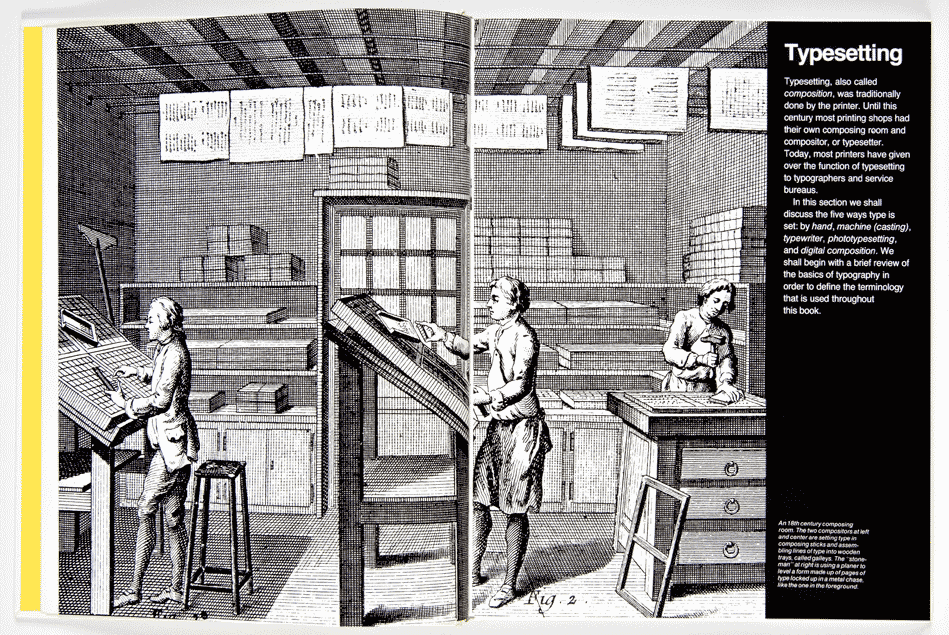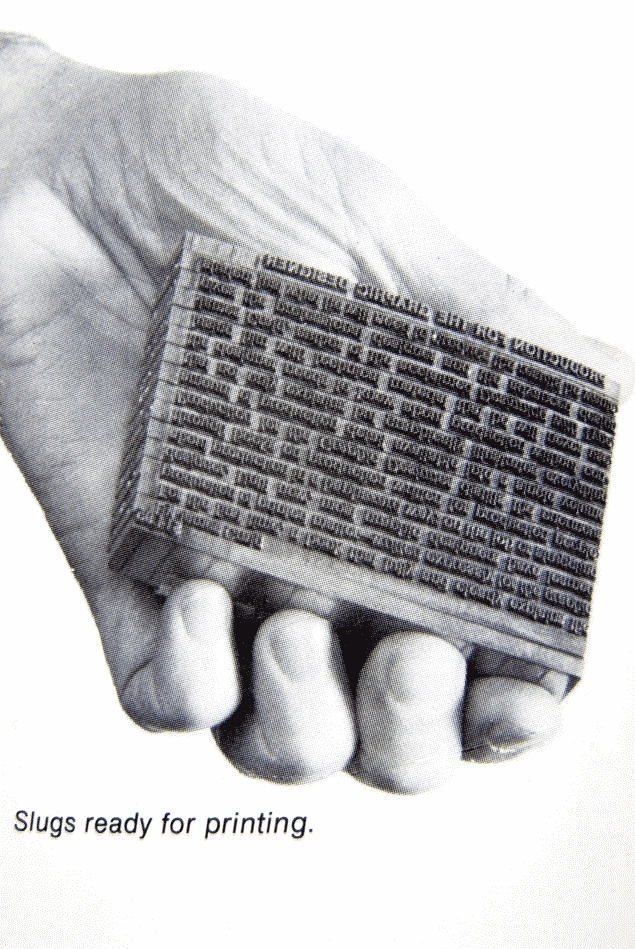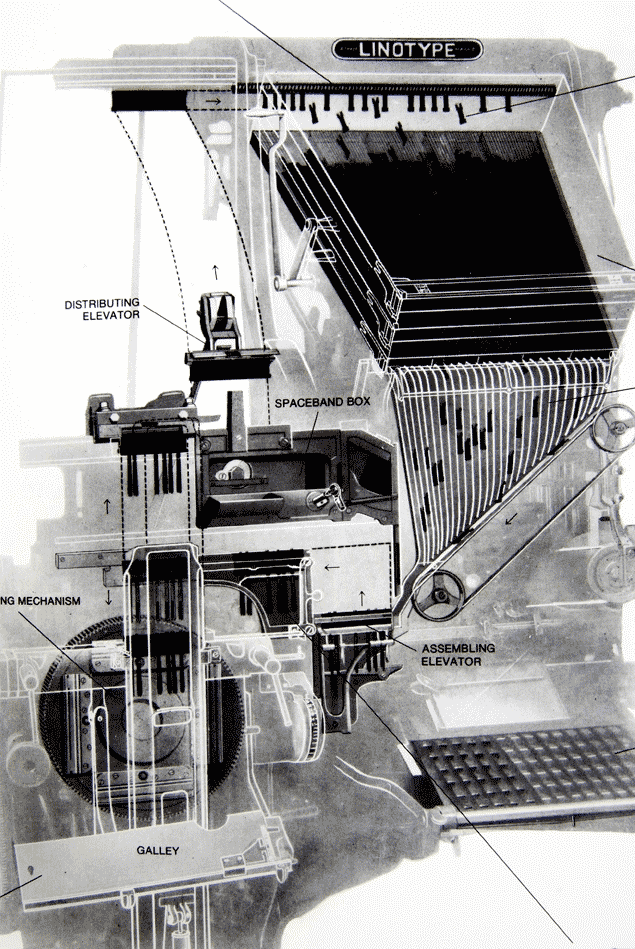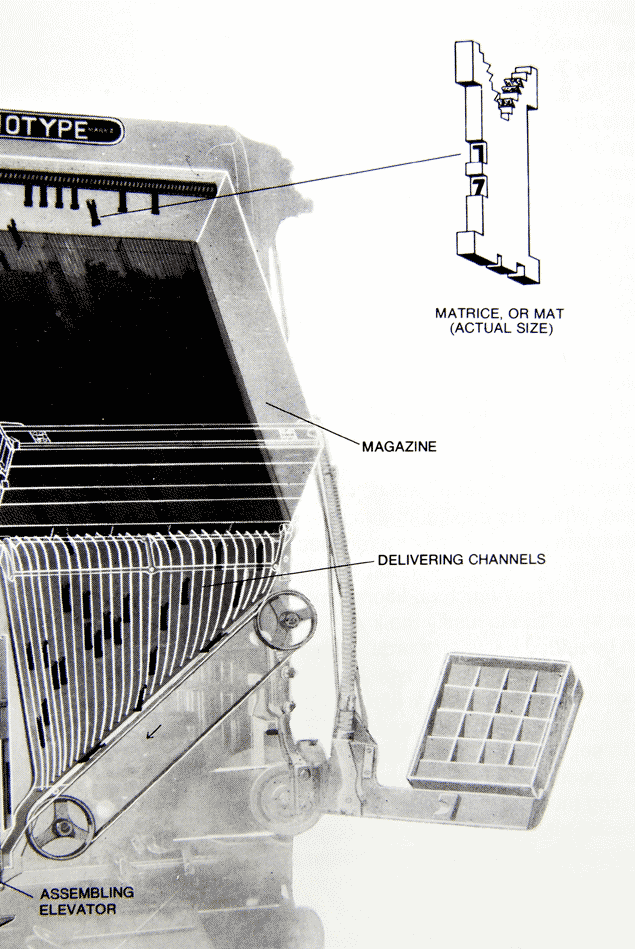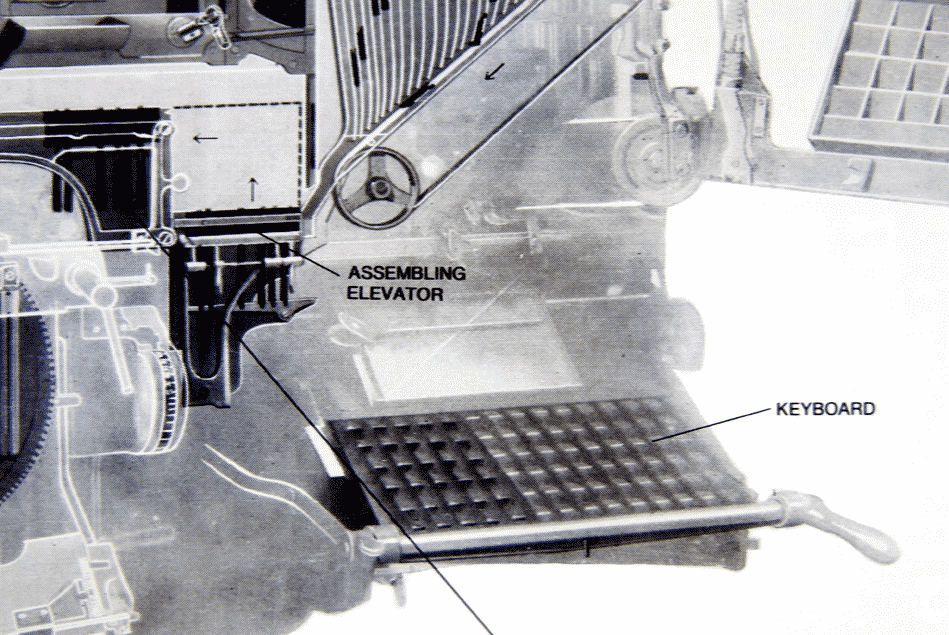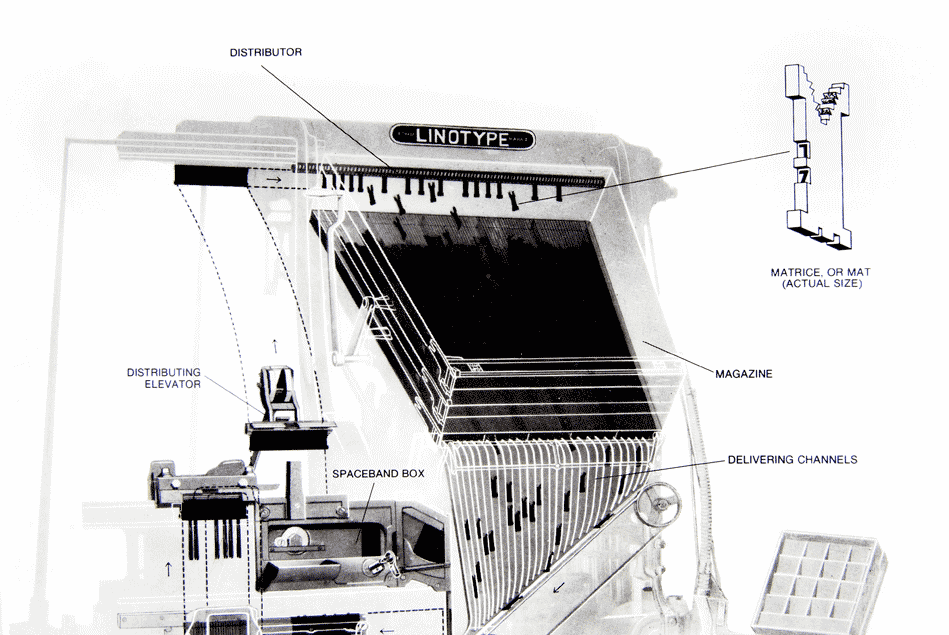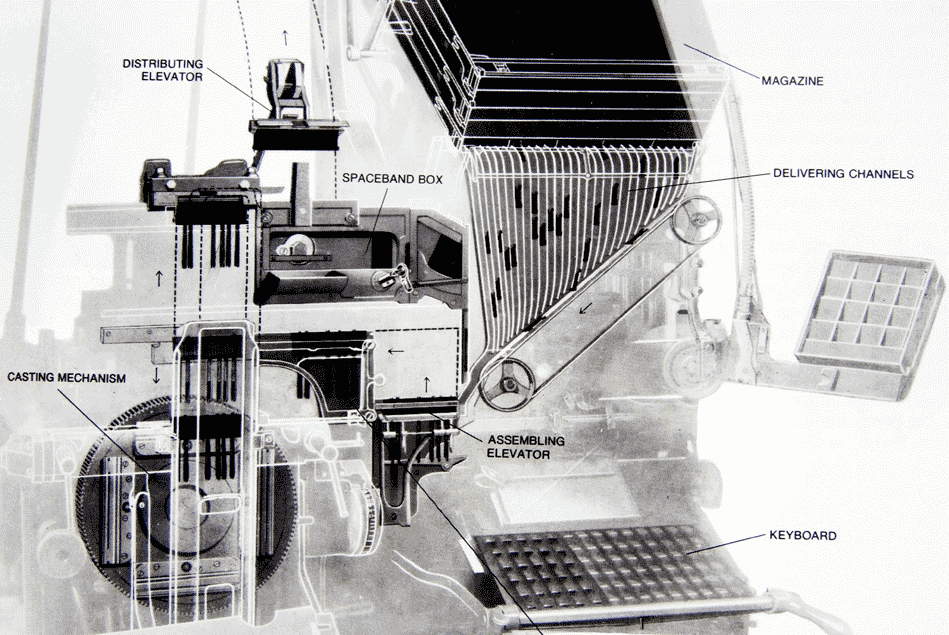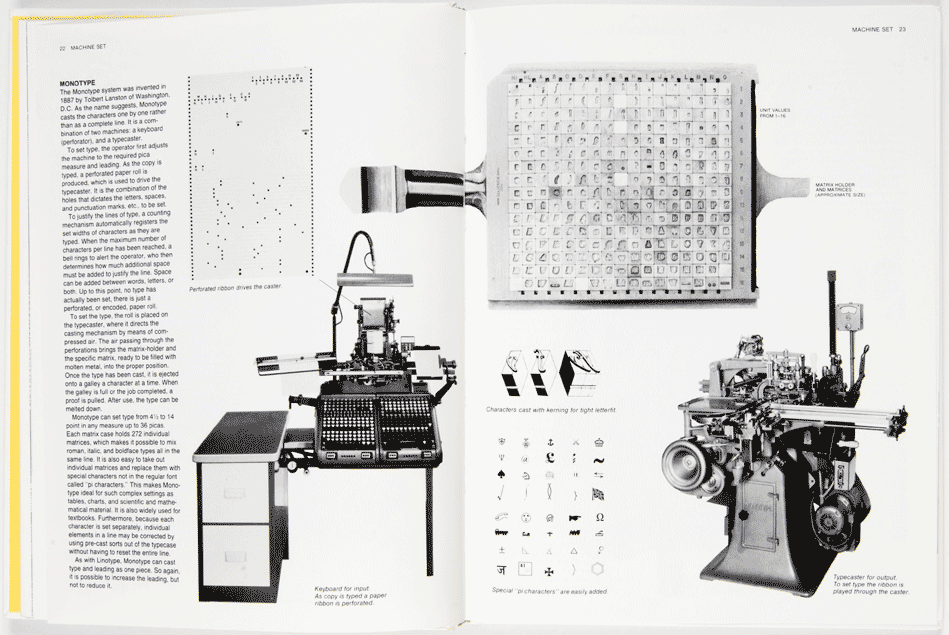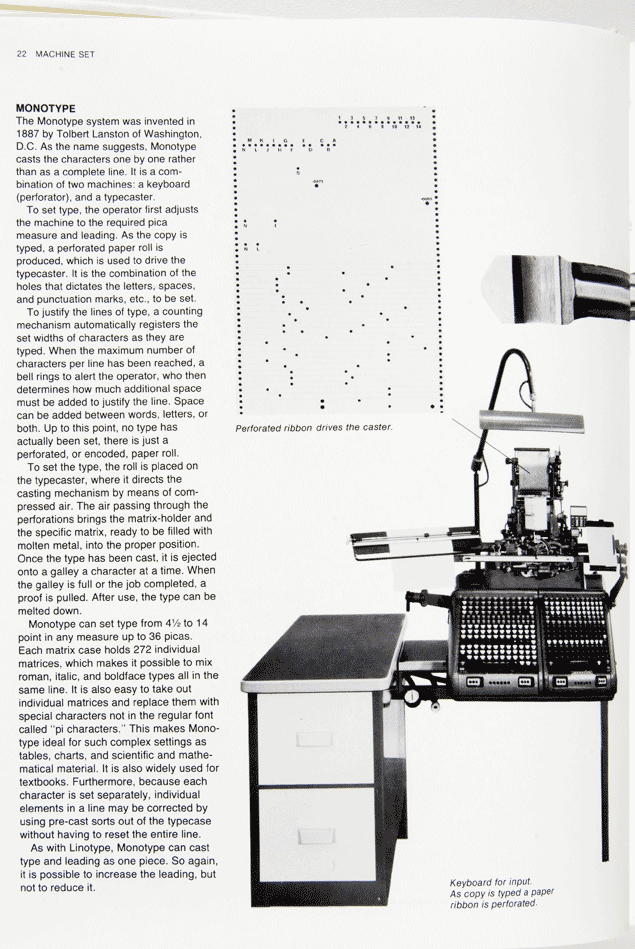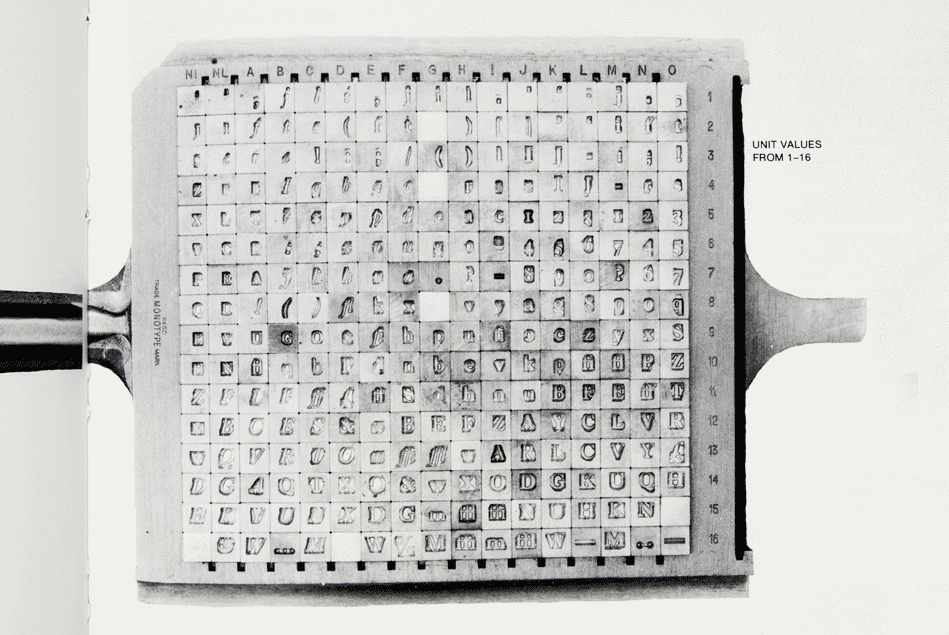
Production graphique pour les graphistes et designers | Typographie & plomb, avant la photocomposition
Comme je vous l’annonçais hier, voici une histoire de la Production Graphique que j’ai repris de l’excellent ouvrage (si ce n’est le meilleur depuis toujours) de James Craig.
De passage à Paris il y a quelques semaines, je lui en ai demandé l’autorisation et pour m’aider il m’a envoyé la deuxième édition qui comprend les débuts du Desktop Publishing communément appelé et mal à propos la PAO.
Voici donc une première partie qui recouvre la composition manuelle (au composteur), le titrage avec les machines Ludlow et la composition mécanisé avec les Linotypes et Monotypes.
gravure du XVIII montrant un compositeur typographe debout devant une casse de plomb
presse à épreuve
fabrication d’encre, d’après une gravure chinoise Ve siècle
fabrication du papier
pupitre de graveur
un «type», un caractère en plomb mobile. Où l’on voit la lettre en relief sur le «Talus», l’encoche devant, servait au «typo» à reconnaître le sens de la lettre, qui est fondue à l’envers sur le talus.
des morceaux de plomb, sans aucun relief, servant juste d’espaces entre les mots ou les poncutations
la moindre interlettrage si aisée aujourd’hui nécessitait de composer des espaces physiques entre les lettres. Un blanc est donc un signe, que les compteurs de «traitement de textes» continuent encore à comptabiliser.
des espaces-lignes, en cuivre pour séparer les lignes (surinterlignage) ou paragraphes (espaces après). La hauteur de ces lingots est évidemment moindre que celle des lettres, ainsi ils ne touchent pas le papier lors de l’impression. (il me semble me souvenir que cette hauteur est approximativement de 23mm). L’épaisseur des filets se mesure en points Didot ou Pica chez les anglo-saxons. Toujours d’actualité sur nos supers Mac ou PC.
un em est l’équivalent de notre cadratin en France. Il est égal au carré de la hauteur du corps, ce qui fait qu’il est proportionnel à chaque dimension de la composition. Aujourd’hui encore ces mesures sont en vigueur dans les logiciels les plus notoires, Quark X-Press, InDesign, PageMaker etc. Le cadratin est subdivisé en unités, c’est ce qu’expliquent les schémas ci-dessus.
Le «composteur», cette règle métallique que tient le compositeur, dans laquelle il glisse les caractères en les lisant à l’envers. La vitesse de composition dite manuelle pouvait atteindre en moyenne 1300-1500 signes à l’heure. Cette vitesse ne tient pas compte du temps qu’il fallait pour ensuite, après le tirage des épreuves, à «redistribuer» les lettres dans les casses.
une casse californienne
une presse à épreuve moderne (aux alentours des années 50)
la «Forme» de composition. Les lignes étaient maintenues par des lingots serrés avec une clé, pour résister à la force des presses à épreuve.
voici la forme et la clé qui sert à resserrer les lingots faisant bordure.
une presse à épreuve plus moderne. Rapidité, précision et régularité de la pression en sont les principaux atouts. Il servait dans des ateliers de composition à façon. Certains de ces ateliers avaient encore le vent en poupe dans les années 60-70, comme Deberny& Peignot au 14 de la rue Cabanis en face de l’hôpital Sainte-Anne.
une composition corrigée avec les signes typographiques et ci-dessous le résultat, une fois recomposé le texte en tenant compte des indications du correcteur.
les signes anglo-saxonnes de la correction typographique et leur équivalent français.
la machine à composer Linotype inventée en 1886 par Ottmar Mergenthaler à Baltimore. Elle fut suivi de près par l’InterType développée vers 1911. Ces machines composaient non des lettres mais des lignes, litéralement des Line-of-Type, fondus d’un bloc. Puis les bloc-lignes étaient montés sur le «marbre», une table métallique où l’on pouvait «tacquer» correctement toutes les lignes. La partie gauche de la machine est la fondeuse. L’on peut imaginer les émanations d’antimoine que respiraient les typographes clavistes de l’époque. On ne parlait pas encore de santé professionnelle, ni de risques majeures et les maladies comme le «saturnisme» étaient bien souvent tournés en ridicule, traités au canons de rouge pour oublier les souffrances physiques.
un paragraphe en lignes-blocs sortis d’une Linotype
schéma de fonctionnement où l’on voit que le «magasin» qui contient les matrices des lettres laissent filer celles-ci au fur et à mesure de la composition. Une fois que ces matrices ont servi à fondre une lettre elles remontent dans le magasin.
la fondeuse Monotype
des caractères fondus avec des espaces négatives pour une approche plus équilibrée (kerning).
machine à composer des titres en plomb: le Ludlow